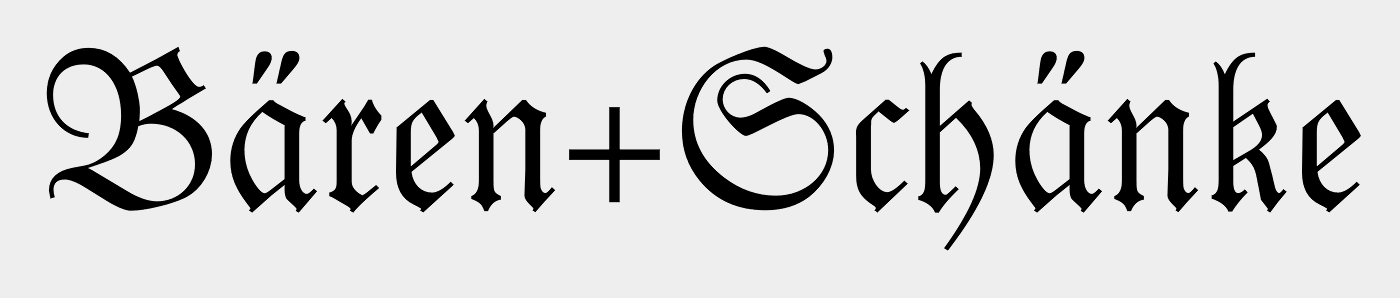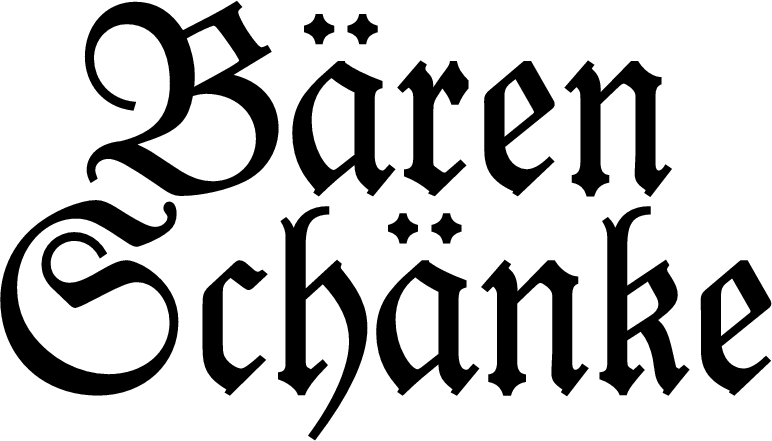
Suche Variante von FRAKTUR!
Bin auf der Suche nach dieser Schiftart. Müsste eine Variante von FRAKTUR sein, finde jedoch keine Übereinstimmung z.B. mit den Punkten über dem "ä". Danke schon mal für die Hilfe.....
Luthersche Fraktur als historische Vorlage ist, denke ich, auch korrekt. Aber die betreffende Digitalisierung läuft nicht unter diesem Namen.
Und dann sind diese "Kreuzschrauben-Punkte" ja eigentlich als Fraktur-Umlaute falsch und eigentlich vom Satzzeichen gemopst. Richtiger sind eigentlich die mehr Strichartigen, schließlich stammen die deutschen Ümläutö ;-) ja vom übergesetzten (kurrent-) e ab, das dann zu zwei Strichlein, und später zu 2 Punkten vereinfacht wurde